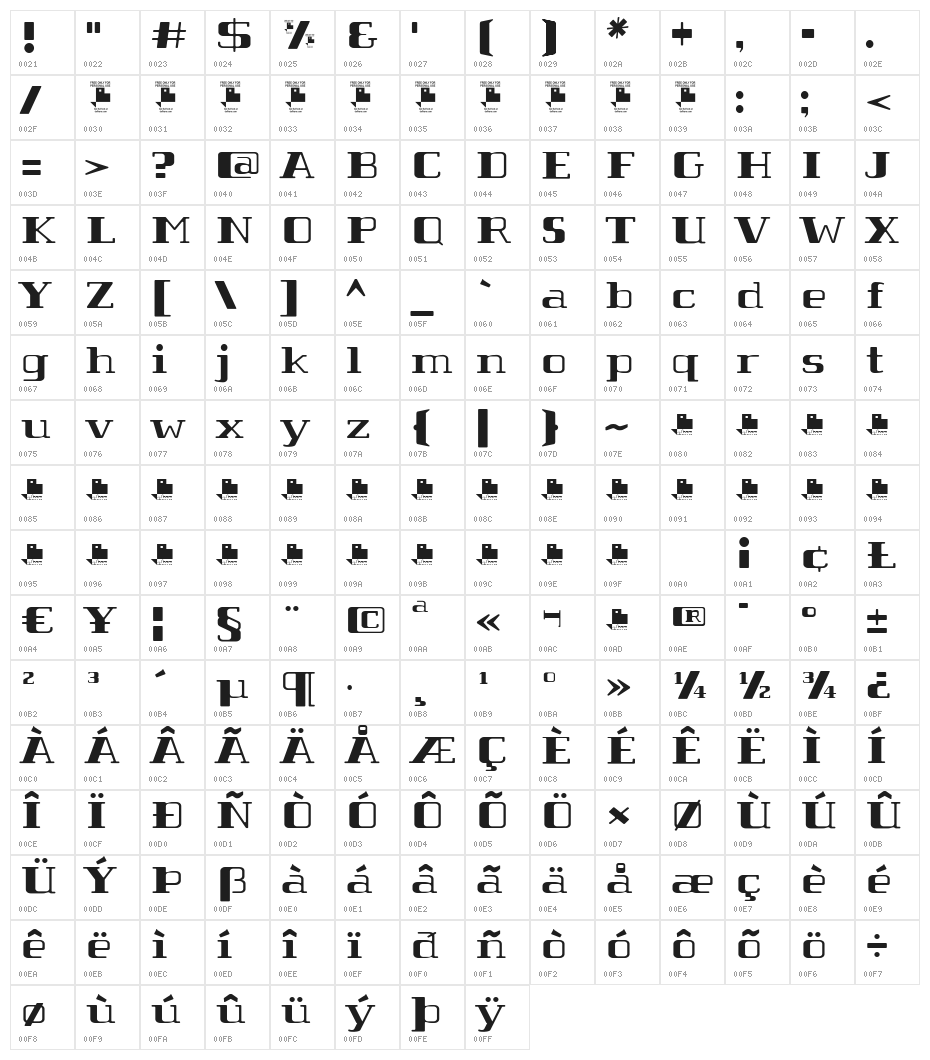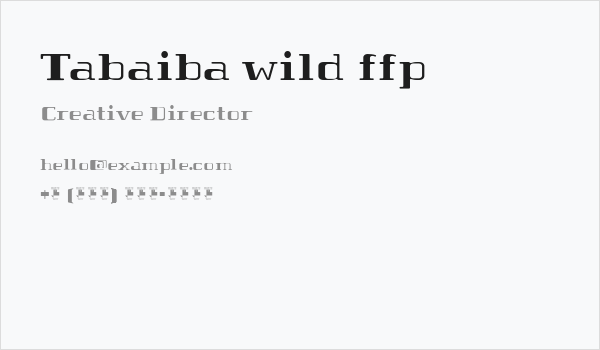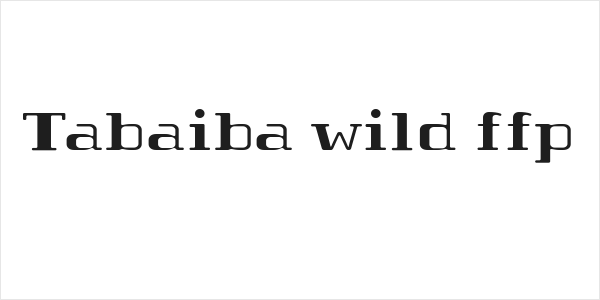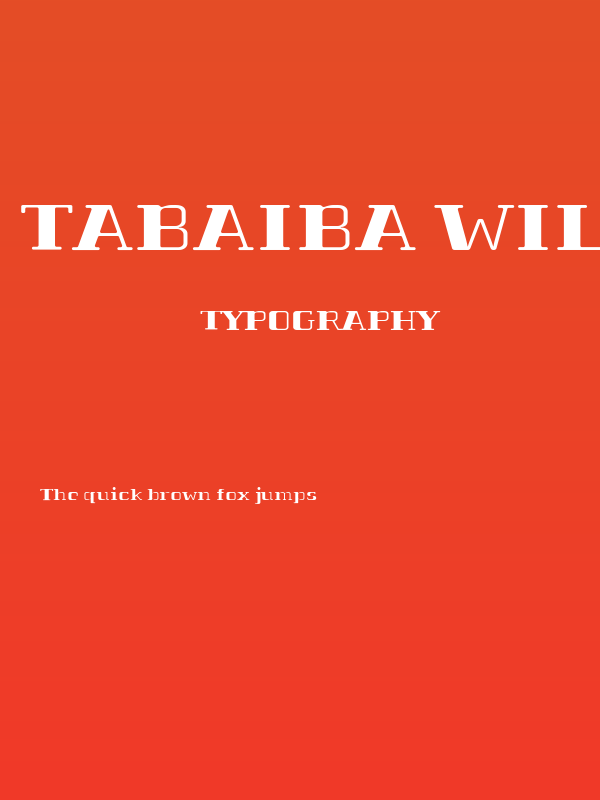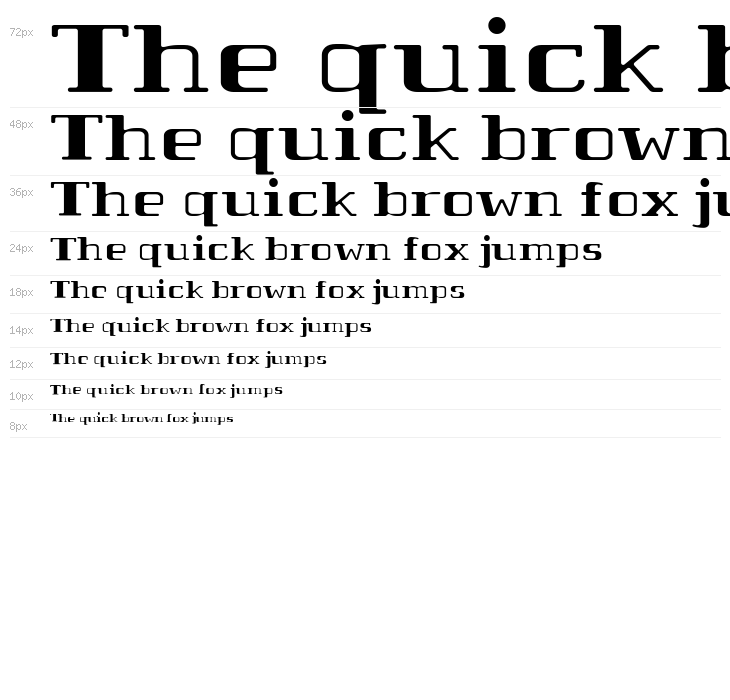
Tabaiba wild ffp Font
| Vorgeschlagene Projekte | Ideal for branding, headlines, posters, and editorial design where a strong, modern serif is needed. |